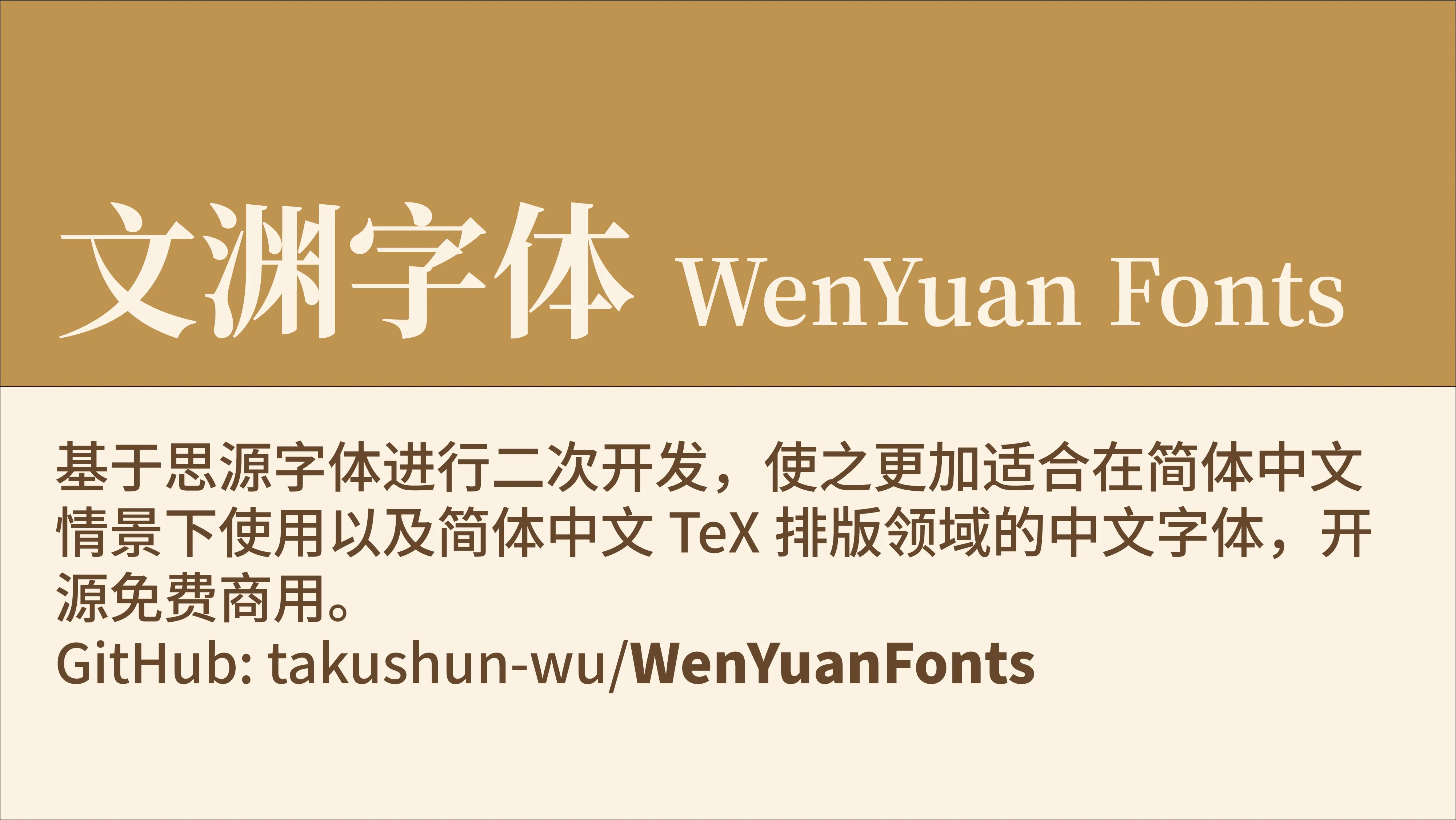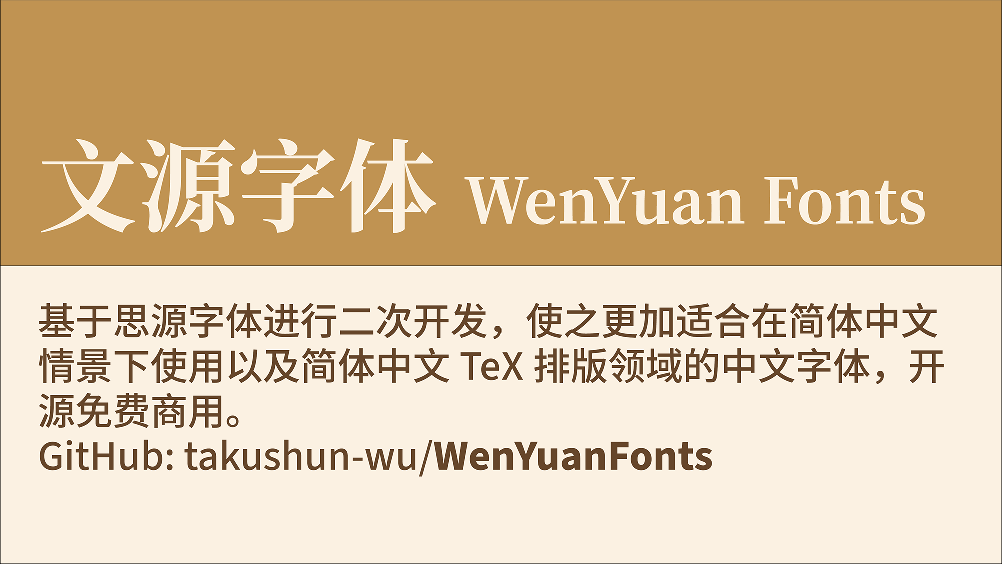
文渊黑体 SC
别称:WenYuan Sans SC
概述
文渊字体
文渊字体包含三大字体系列:文渊黑体、文渊宋体和文渊圆体。这些字体都是基于思源黑体和思源宋体二次开发而来。文渊字体支持的大多数汉字(GB 18030-2022 实现级别 2 范围内全部)采用中国大陆字形标准,且非汉字符号迎合简体中文一般使用习惯。以上字体均采用 OFL 协议,任何个人与团体均可免费商用。
虽然 Adobe 和 Google 联合发布的思源黑体和思源宋体对整个东亚的设计和出版领域起了十分重大的影响,同时也开启了基于中日韩文字的开源字体的新局面,但囿于单个字体文件的 65,535 字形数限制等技术原因,同时还要支持中国大陆、港台地区、日本、韩国等多个区域的字形显示,因此某个地区版本的字体有时会出现不符合该地区字形标准的现象。
文渊字体针对以上弊病,对原版思源字体进行优化,改正了错误汉字字形。为减少不必要的空间消耗,移除了原版思源字体的多地区字形支持。同时还根据实际使用需求,增加了一定数量的扩展区汉字(扩展 B~J)。此外还在原版基础上增加了西文字符、拉丁文斜体等功能支持,并在此基础上,新增一个字体家族——文渊圆体。